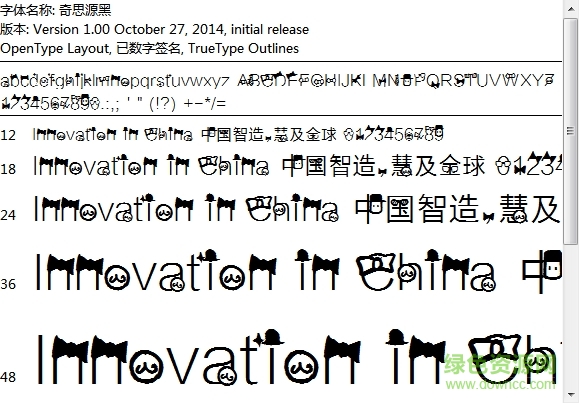
紳士做派字體是奇思源黑推出的一款藝術(shù)字體,有著可愛(ài)的裝飾點(diǎn)綴,給文字增添獨(dú)特的趣味呈現(xiàn),顯得十分生動(dòng)活潑起來(lái),喜歡的朋友可以來(lái)綠色資源網(wǎng)收藏哦!
紳士做派字體有著各種蝴蝶結(jié)、紳士帽、小胡子、四角星點(diǎn)綴,給文字增添了一股活潑之氣,讓你的設(shè)計(jì)更有青春活力的氣息。